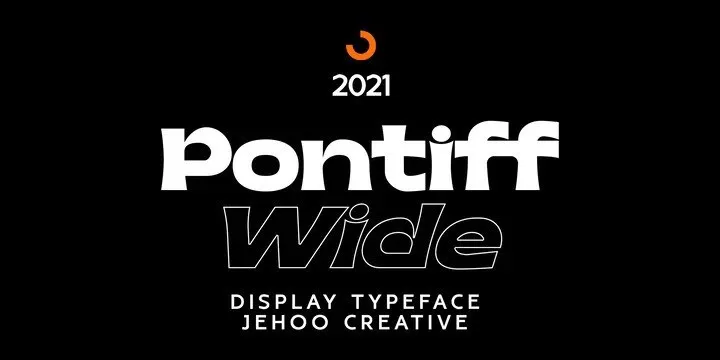
Pontiff Wide Font – Download Grátis
A Pontiff Wide Font é uma elegante serif font que destaca-se pela sua forma arredondada e arredondada, criada para capturar o espírito do neo-vintage. Ideal para qualquer projeto gráfico que valorize os detalhes e a sofisticação de um estilo antigo renovado, esta fonte oferece uma ampla gama de caracteres tanto maiúsculas quanto minúsculas, fornecendo um toque refinado e perfeitamente adaptável à sua necessidade. Como menciona o designer 99designs, Jehoo Creative, a Pontiff Wide Font mantém os bordados bem definidos para garantir uma legibilidade excepcional em qualquer tamanho de texto. Seja para aplicativos web ou impressos, esta fonte é uma escolha inteligente que trará um toque diferenciado ao seu design.